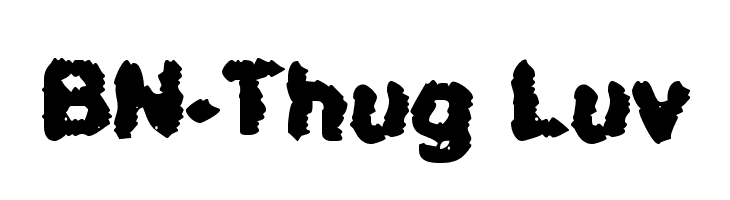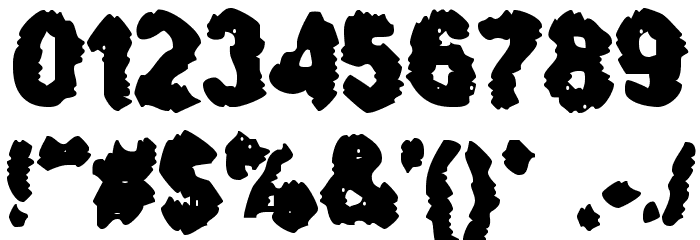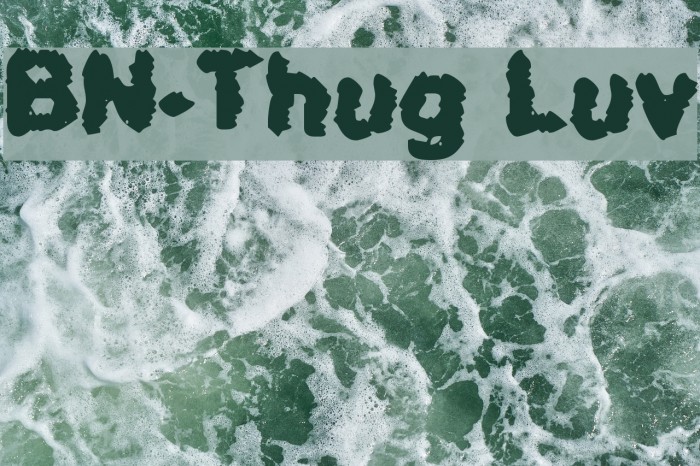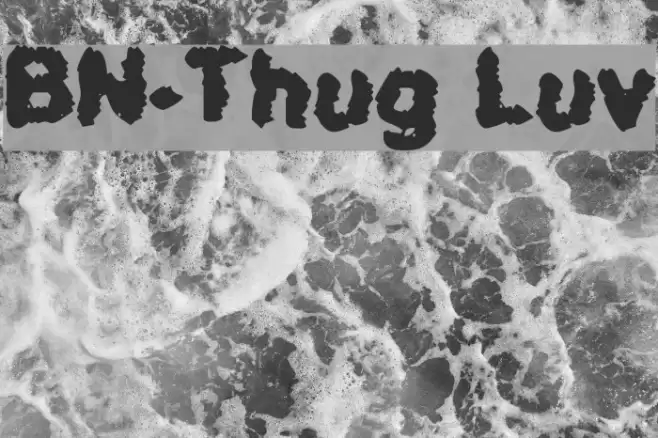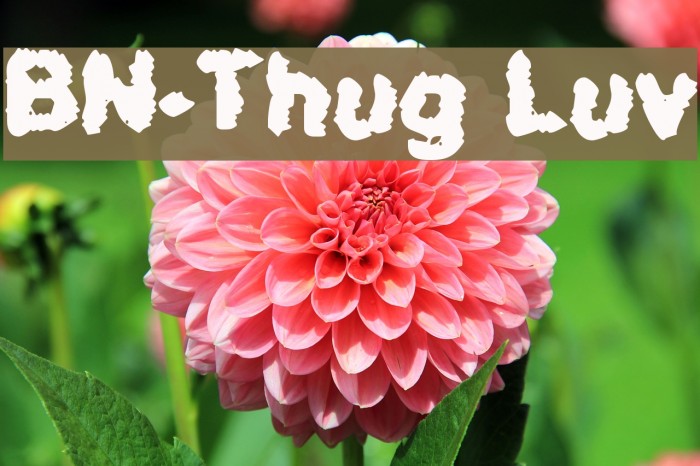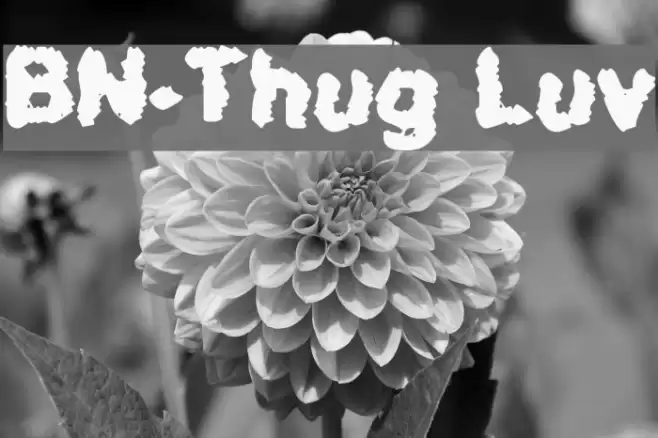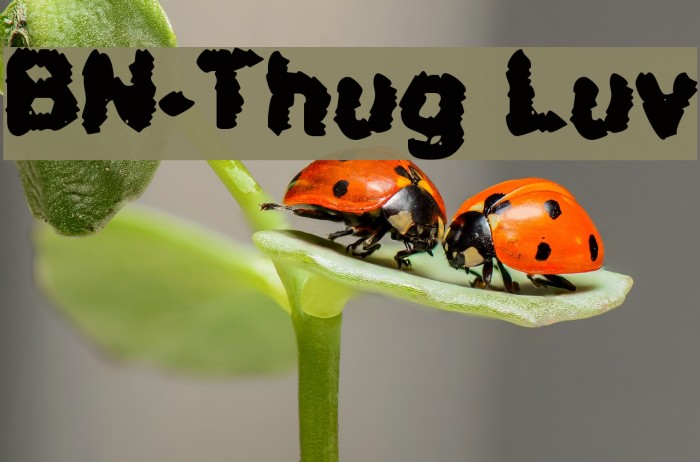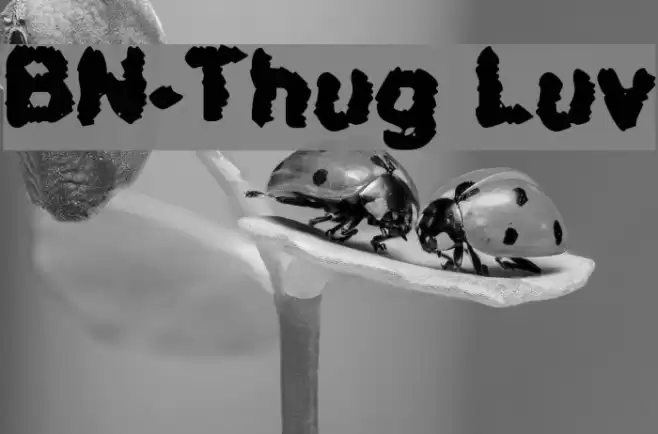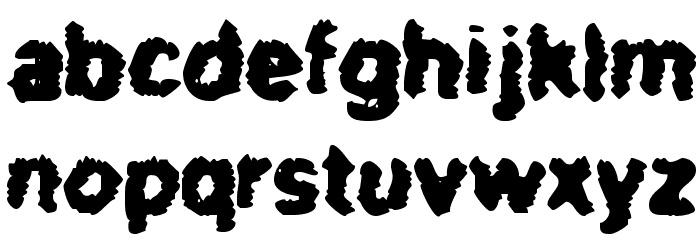
BN-Thug Luv Font
| Категория | Thick |
| Общий стиль | Grunge, Edgy, Rebellious |
| Область применения | Headlines, Posters, Album covers |
| Рекомендуемые проекты | Ideal for music album covers, edgy posters, streetwear branding, and rebellious-themed designs. |